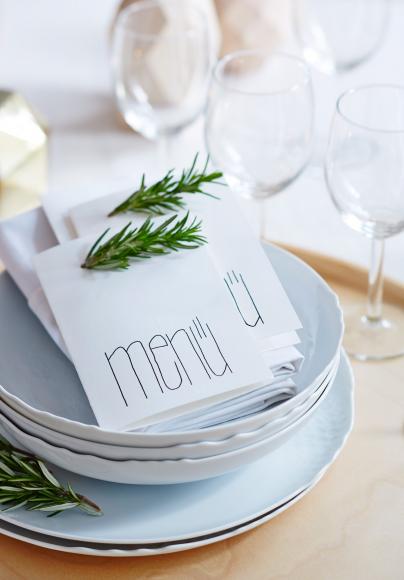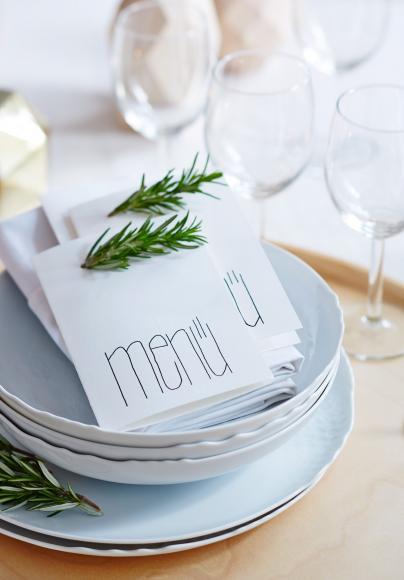
Verzweifelte Braut braucht Hilfe mit einer Schriftart
ich bin gerade dabei meine Hochzeitseinladungen zu gestalten und habe mich bei der Recherche in eine Schrift (s. Bild) verliebt. Kann sie aber nicht finden und auch die kleinen Hilfsmittel brachten kein Ergebnis. Es geht insbesondere um das "Ü".
… Es geht insbesondere um das "Ü".
Um welches? Um das vordere oder das hintere? Die sind unterschiedlich und daran siehst du leider, dass das – wie Ralf schon gesagt hat – handgeschrieben ist.
... und habe mich bei der Recherche in eine Schrift (s. Bild) verliebt. ...